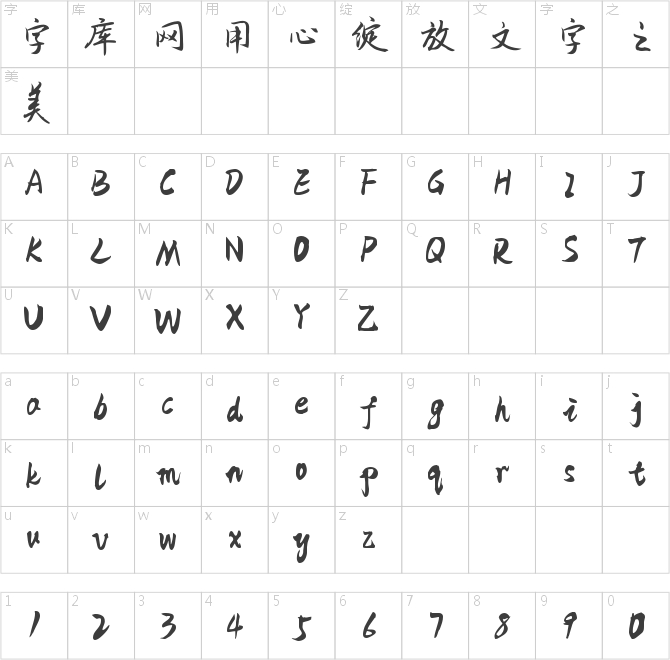
千图笔锋手写体 详情页
字体名称: 千图笔锋手写体
千图笔锋手写体
【千图笔锋手写体】定义为一款清新的创意手写字体。在字形笔画上改变了平直的笔画,用柔和的弧线将字体的柔美发挥的淋漓尽致,字形新颖独特,简洁有力,清新淡雅,文艺范十足。整体采用连笔写法,一气呵成,更显流畅。适用于海报 、影视综艺、文艺宣传等场景。